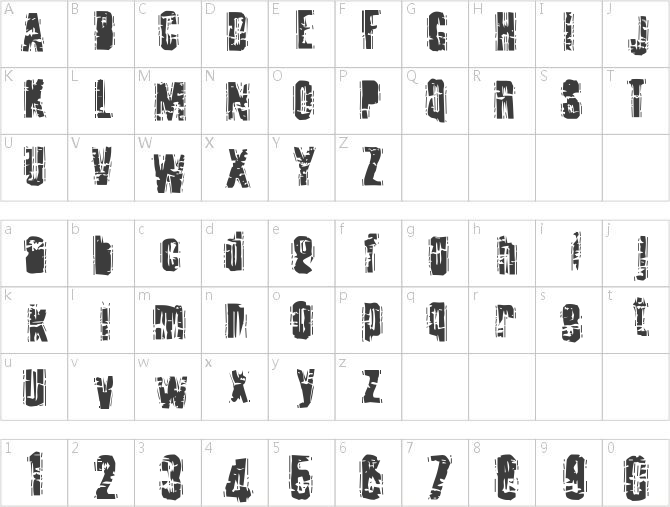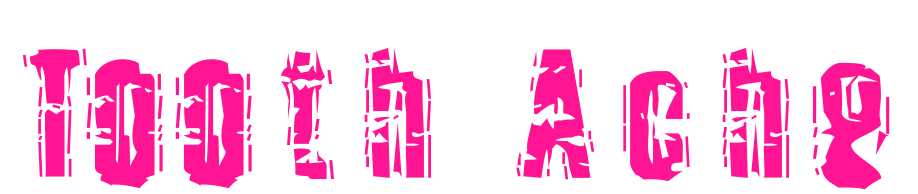
Tooth Ache 詳情頁(yè)
Tooth Ache
Tooth Ache介紹
Tooth Ache字體字庫(kù)是一款讓人賞心悅目、百看不厭的英文字體,適合各類廣告和產(chǎn)品包裝設(shè)計(jì)應(yīng)用,字體大小0.05MB,格式為ttf字體,上傳用戶是手機(jī)洗相,作者/版權(quán)方為未知